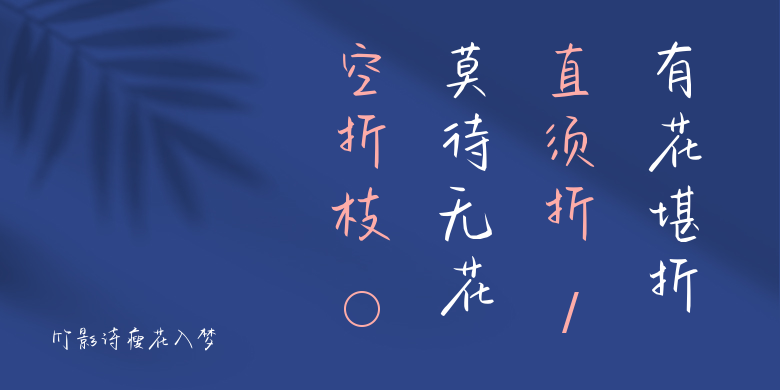
竹影诗瘦花入梦
竹影诗瘦花入梦,这款字体结构工整、笔画清晰,兼顾美观与易读性,适用于标题、正文、海报、包装、LOGO 等多种场景。字形优雅稳定,风格百搭耐看,适配日常排版与创意设计,让文字呈现更舒适、更具质感。竹影诗瘦花入梦一笔一画,皆是细节,以均衡的比例、流畅的线条打造舒适视觉体验,字形端正大气,风格简约现代。无论是商业设计、品牌宣传还是日常排版,都能轻松驾驭,让文字更有格调与力量。竹影诗瘦花入梦字体下载。